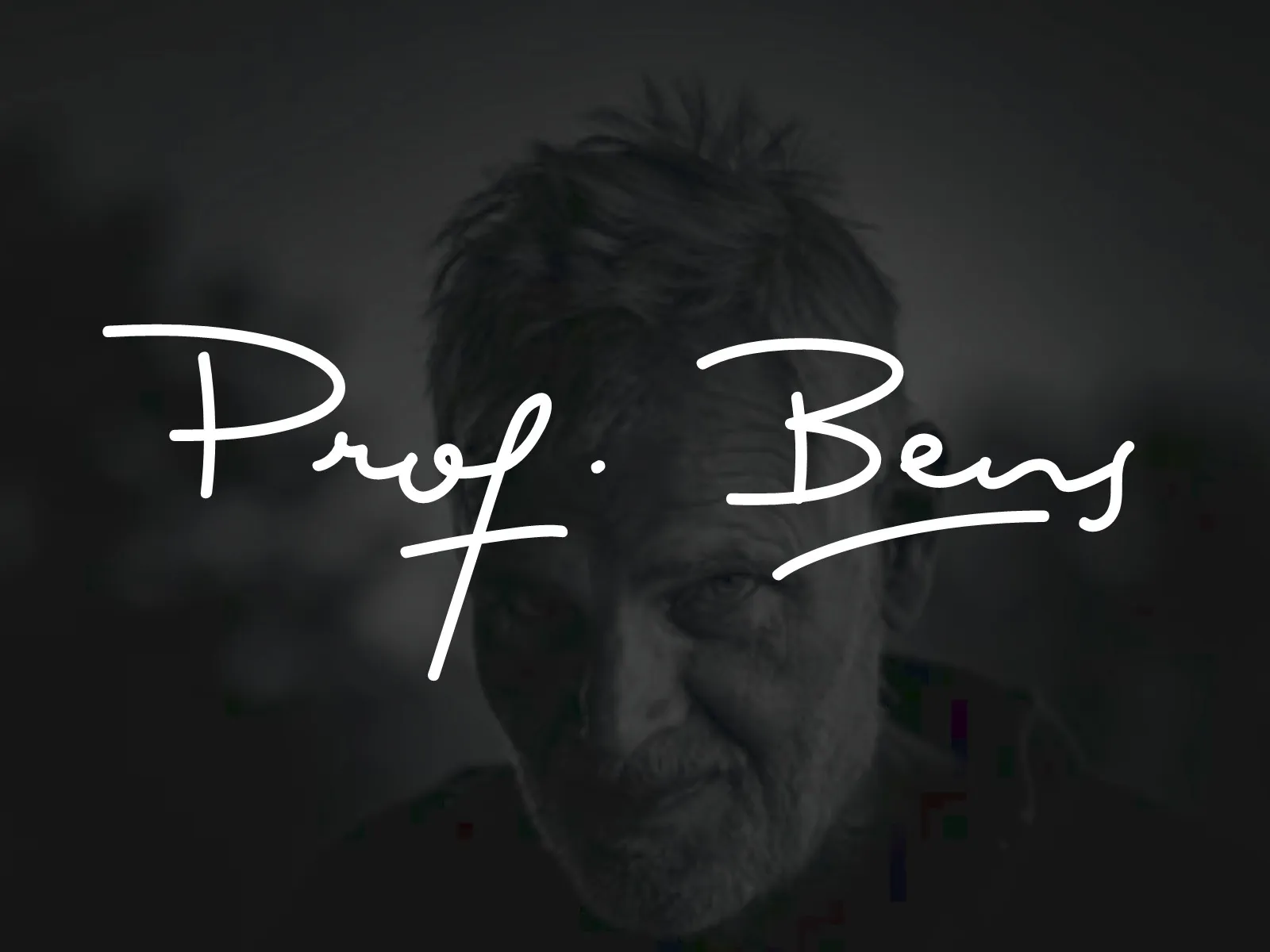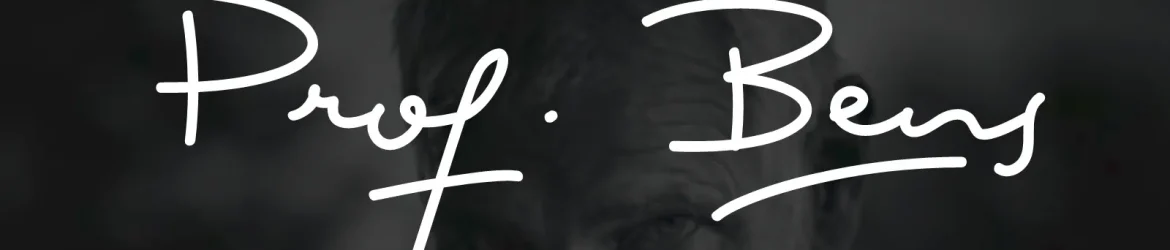
Prof. Bens é uma elegante e fina fonte escrita a mão que transmite sabedoria e profissionalismo. Desenvolvida pelo designer nryntdw, essa fonte se destaca por seu estilo moderno e alternativas sofisticadas que permitem uma adaptação perfeita para cada projeto. Suas ligaturas tornam Prof. Bens ainda mais versátil, permitindo uma apresentação cuidadosa de qualquer texto. Além disso, a opção PUA (Private Use Area) permite que você tenha acesso fácil a todos os símbolos e swashes, oferecendo inúmeras possibilidades criativas sem limite. Prof. Bens é perfeita para se destacar em qualquer projeto, seja de design gráfico, publicidade ou comunicação visual.